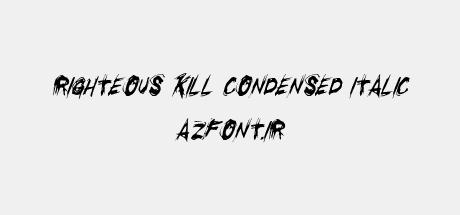
Righteous Kill Condensed Italic
فونت زیبای رایگان Righteous Kill Condensed Italic
قلم زیبای Righteous Kill Condensed Italic از سری قلم های بسیار زیبا برای تایپوگرافی و لوگو تایپ می باشد.این قلم در وزن Condensed Italic و توسط Daniel Zadorozny طراحی و منتشر شده است.